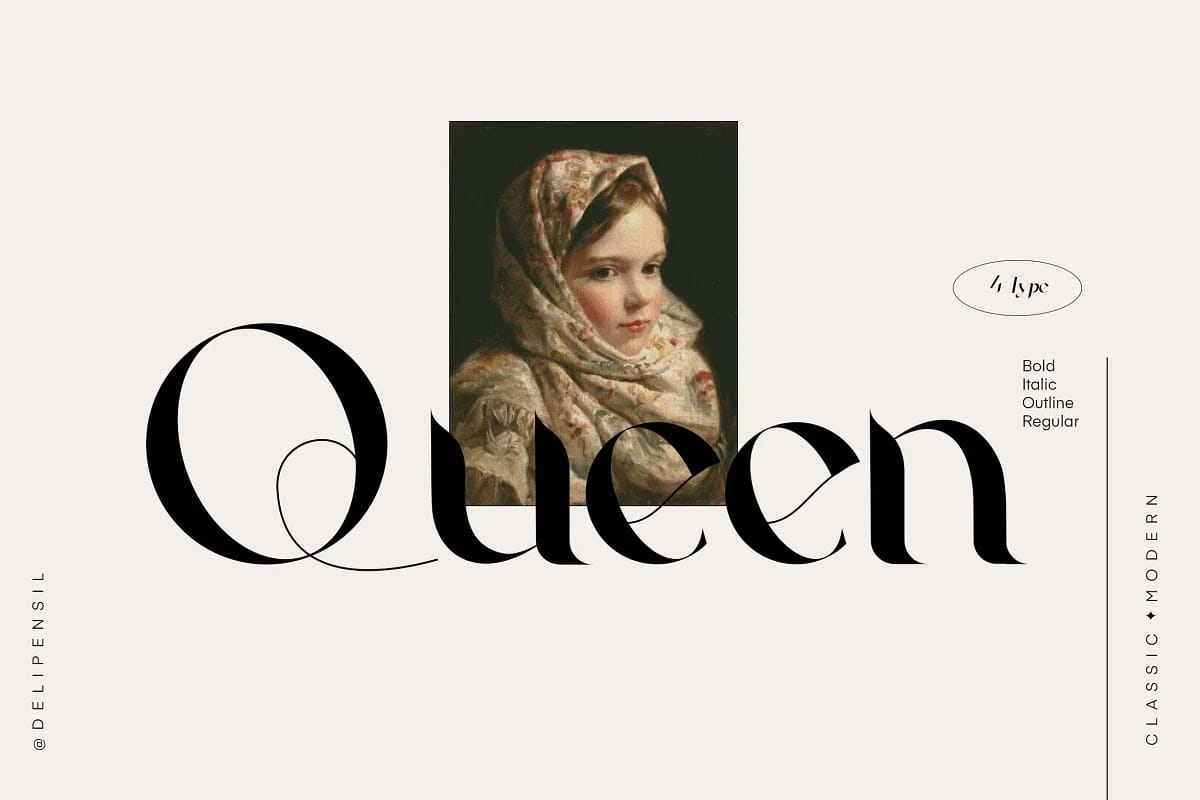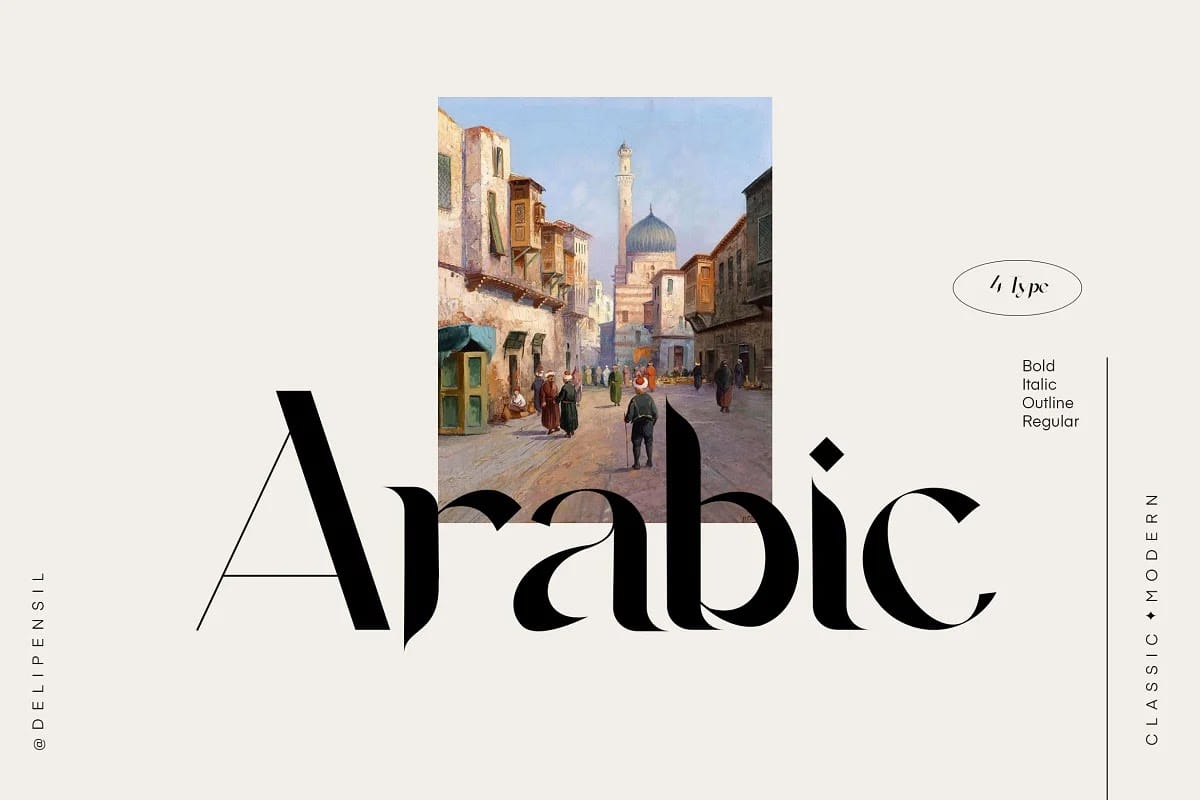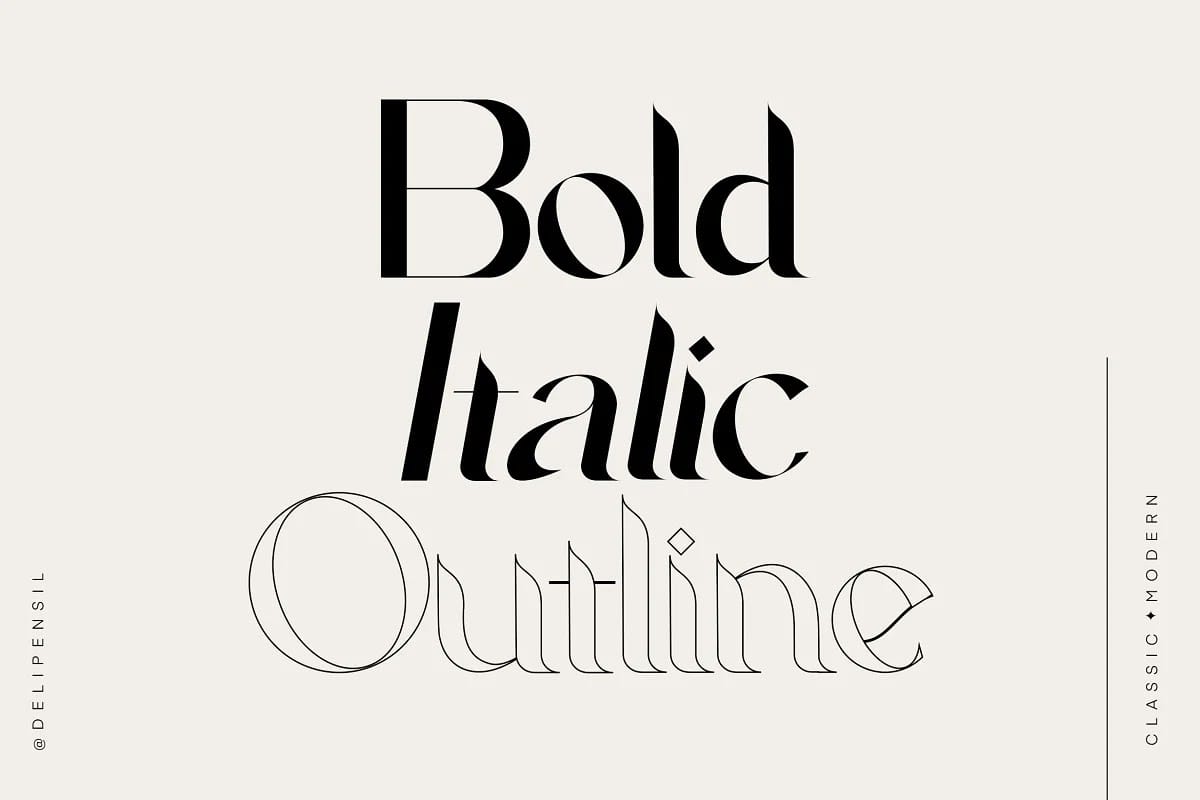
Agoka – Một kiểu font chữ hiện đại cổ điển đẹp mắt 👑
Font chữ Agoka Modern Classic Typeface được thiết kế thanh lịch, sạch sẽ và ấn tượng, với sự kết hợp hoàn hảo này bạn có thể sử dụng cho bất kỳ thiết kế nào cho logo, tiêu đề, sách bìa, tạp chí, trang web của bạn và nhiều hơn nữa